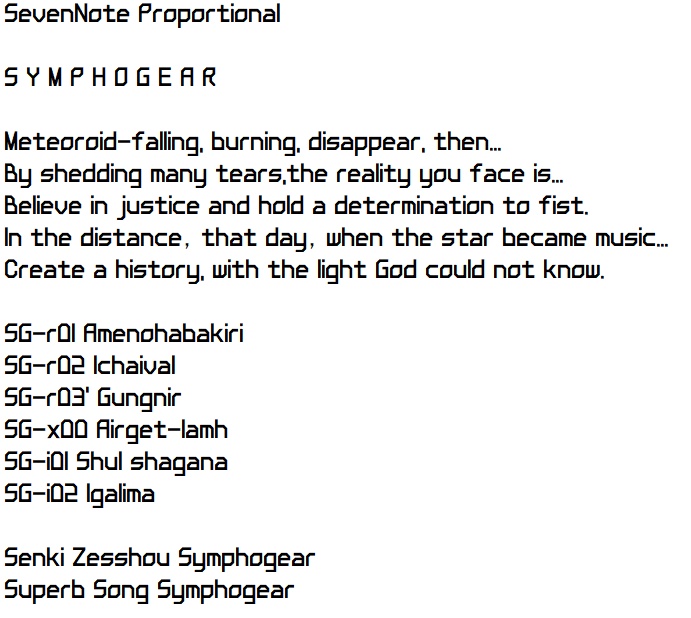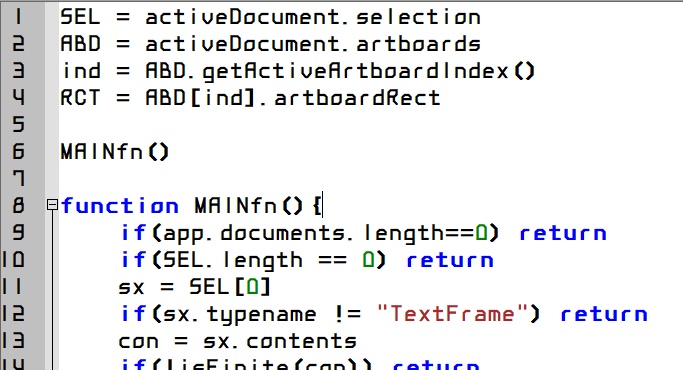
【フリーフォント】SevenNote
「SevenNote」は、戦記絶唱シンフォギアのフォントを再現した非公式フォント(TrueType)です。 個人的に作っていたモノがある程度形になったので無料公開します。 商用利用NG、同人利用OKです。 詳細はRead Meを参照してください。 "SevenNote" is an unofficial imitation font of Senki Zessho Symphogear. You can use this font for non-commercial and personal use only. Not allowed for commercial use. Please read the included "Read Me" file for details.